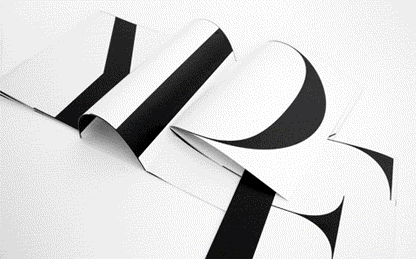
Homework is an independent graphic design studio and consultancy that focuses on art direction, visual identity and communication for lifestyle, fashion and cultural clients. Homework was established in 2002 by Jack Dahl. Jack Dahl was responsible for kickstarting a visual presence and direction for international mens fashion publication HE magazine and Cover magazine (Copenhagen). Among others Jack has worked with Self Service magazine and Work in Progress advertising design studio (Paris) on some of todays leading fashion references including Jil Sander, Prada, Pucci, Chloé, Celine, Colette and Virgin Records.
Ce que j’aime ici? la simplicité sans doute, mais aussi cette osmose entre typographie, recherches graphiques où les codes d’élégance de la mode imprègnent chaque travail, les contrastes, les rapports monumentalistes, les pleins et déliés, les caractères à sérifs qui se mélangent sans cesse avec les modernes sans. On n’est pas loin de l’héritage de Lubalin et les Danois sont luthériens comme la plupart des américains des deux côtes Atlantique et Pacifique. Lorsqu’on songe que cette religion domine dans tous les pays où l’excellence typographique a été porté aux nues, on peut se demander si le Dieu de Calvin (pas Klein), et de Luther (pas King) ne serait pas typographe un peu. Dès fois.